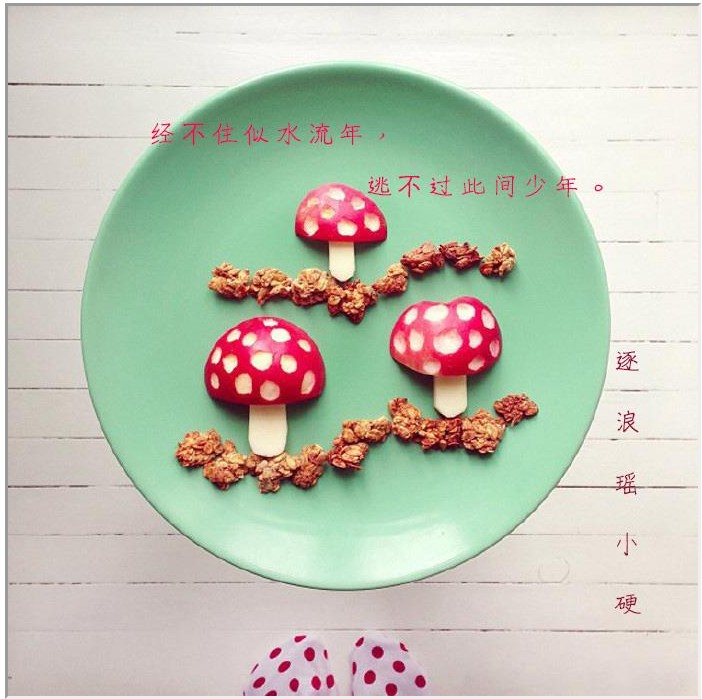
作品设计背景与理念
这是一款简体字库,共有6861个汉字(含基本英文字母及符号),基于GB18030标准。
本案字库全部基于手写,先是于逐浪智写(v.ziti163.com)平台进行会员注册,通过触控笔(微软surface pro3)写作,然后发布,最后下载合成,通过智能的APP创作,是一种全新的尝试,极大的开拓了汉字字库的创作效率和方法,引领业界创新。
字体风格规矩中通,起笔严谨,后期合成与间隔也相当科学规范,是较好的硬笔字体设计作品。
本款“逐浪瑶小硬”是一款书写很新颖的字体,字体大方,适合各种设计作品使用!欢迎下载!